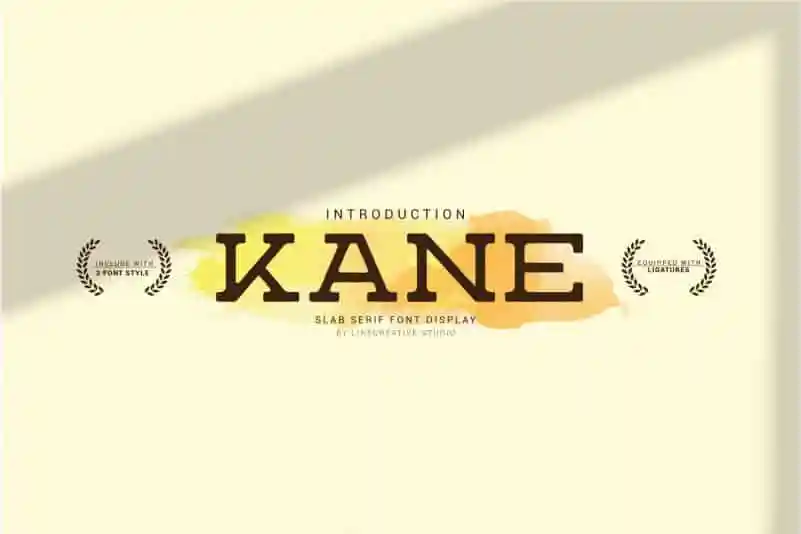
Kane Slab Serif Font – Download Grátis
A Kane Slab Serif Font é uma escolha perfeita para quem procura um estilo serif que se destaca com elegância moderna. Com seu carácter robusto e acentos levemente curvados, essa fonte transmite uma sensação de limpeza e sofisticação. Ela não apenas oferece a versatilidade necessária para trabalhos de design, mas também incorpora características únicas como ligaturas, permitindo que os criadores abordem projetos com liberdade e inovação sem limites. Esta fonte é ideal para aplicações em Latin Western Europe, adaptando-se com facilidade às demandas estilísticas dos designs digitais atuais. Seja você um designer gráfico ou web developer, Kane Slab Serif Font do designer ari é uma escolha inteligente para enriquecer suas criações de design.